봄이 온 걸 한번에 알겠어요! 봄 느낌 듬뿍 담은 폰트 추천
봄봄봄 봄이 왔어요~ 찬바람이 언제 불었냐는 듯 따스한 봄바람이 불고 만개한 봄꽃에 봄의 정취가 한껏 느껴지는 요즘이에요! 이 봄을 더욱 만끽하고자 산돌구름이 봄 향기 가득한 폰트 4종을 모아봤습니다.
1. 산돌 / Sandoll 늦봄
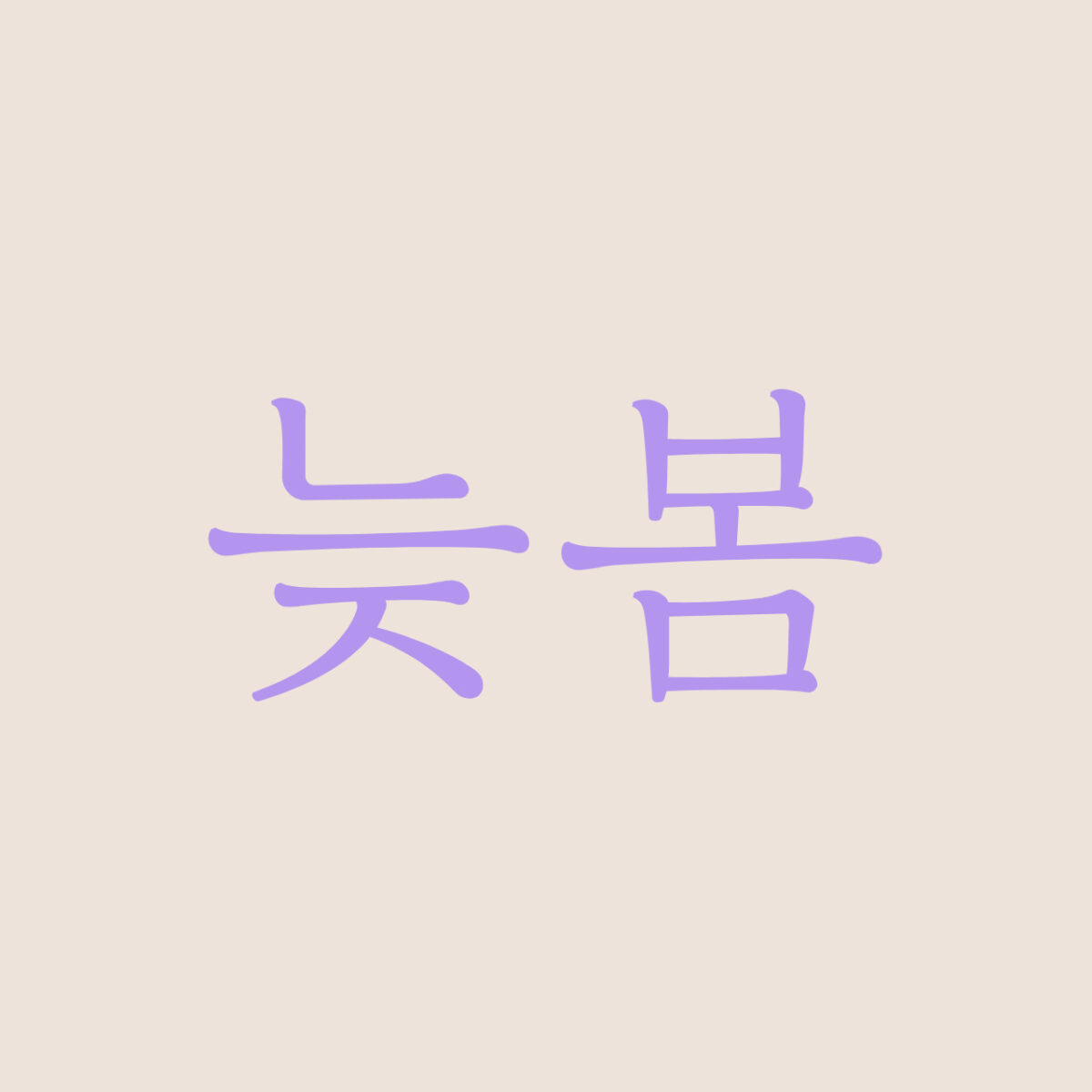
‘Sandoll 늦봄’은 붓글씨 특유의 감성을 부드럽게 살린 폰트입니다. 자연스러운 획의 꺾임과 손글씨의 필순을 따른 디자인으로, 정갈하고 정성스러운 느낌을 줄 수 있어요. 일반 Light, Medium 2종과 아주 가는 White, 붓 자국처럼 장식을 남긴 Black 2종까지 총 4종을 지원하여 다양한 스타일로 선택하여 사용할 수 있어요. 브로슈어나 포스터, 간행물 등에 사용하여 봄의 따뜻한 감성을 표현해 보세요.
2. 디엑스코리아 / DX봄바람
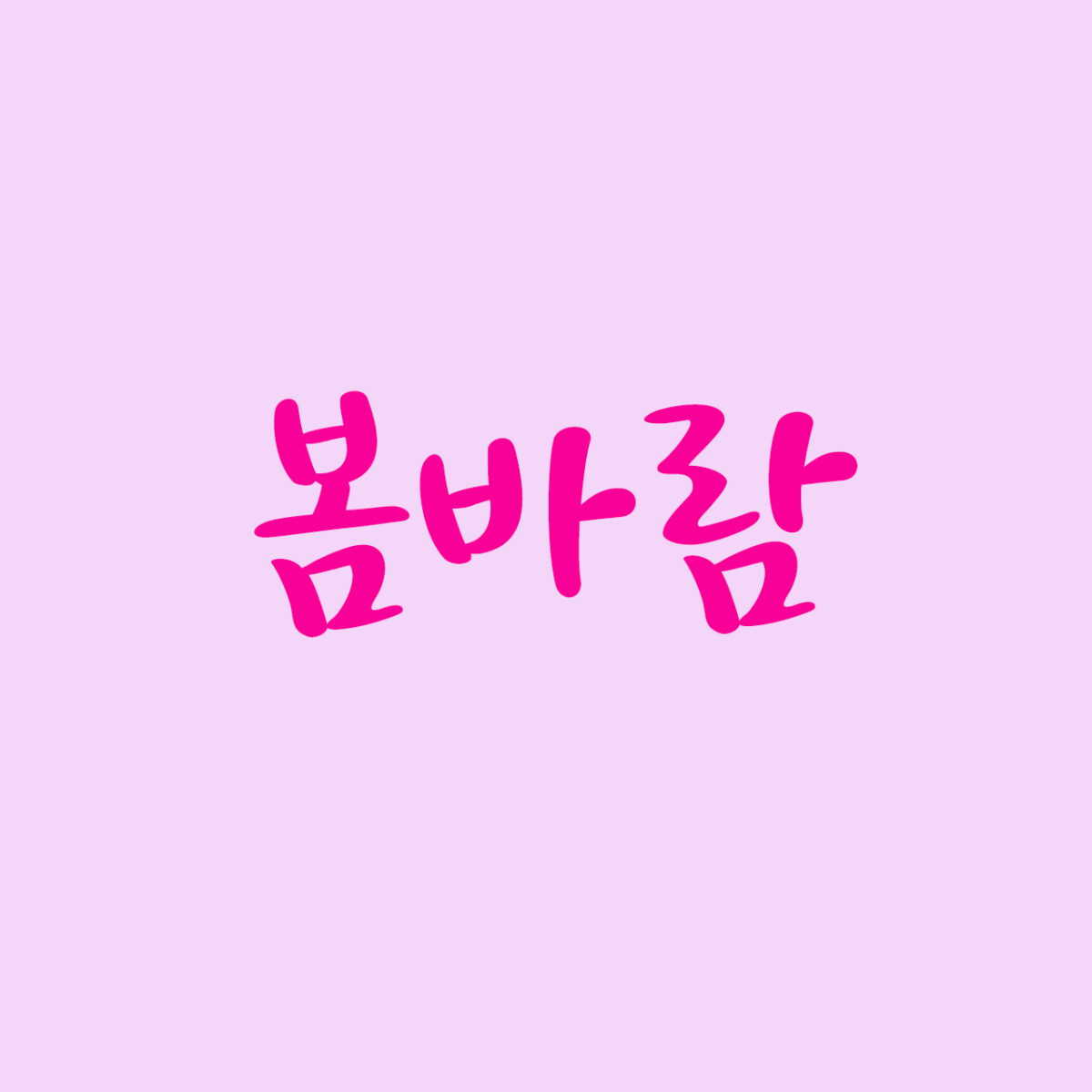
‘DX봄바람’은 이름 그대로 살랑거리는 봄바람이 느껴지는 손글씨 폰트입니다. 가늘고 두꺼운 획이 적절하게 조화를 이루어 자연스럽고 편안한 인상이 느껴져요. 방송 자막이나 타이틀, 봄과 관련된 행사 포스터나 현수막에 사용하는 것을 추천해요!
3. 타입세트컴퍼니 / TSC봄을닮아
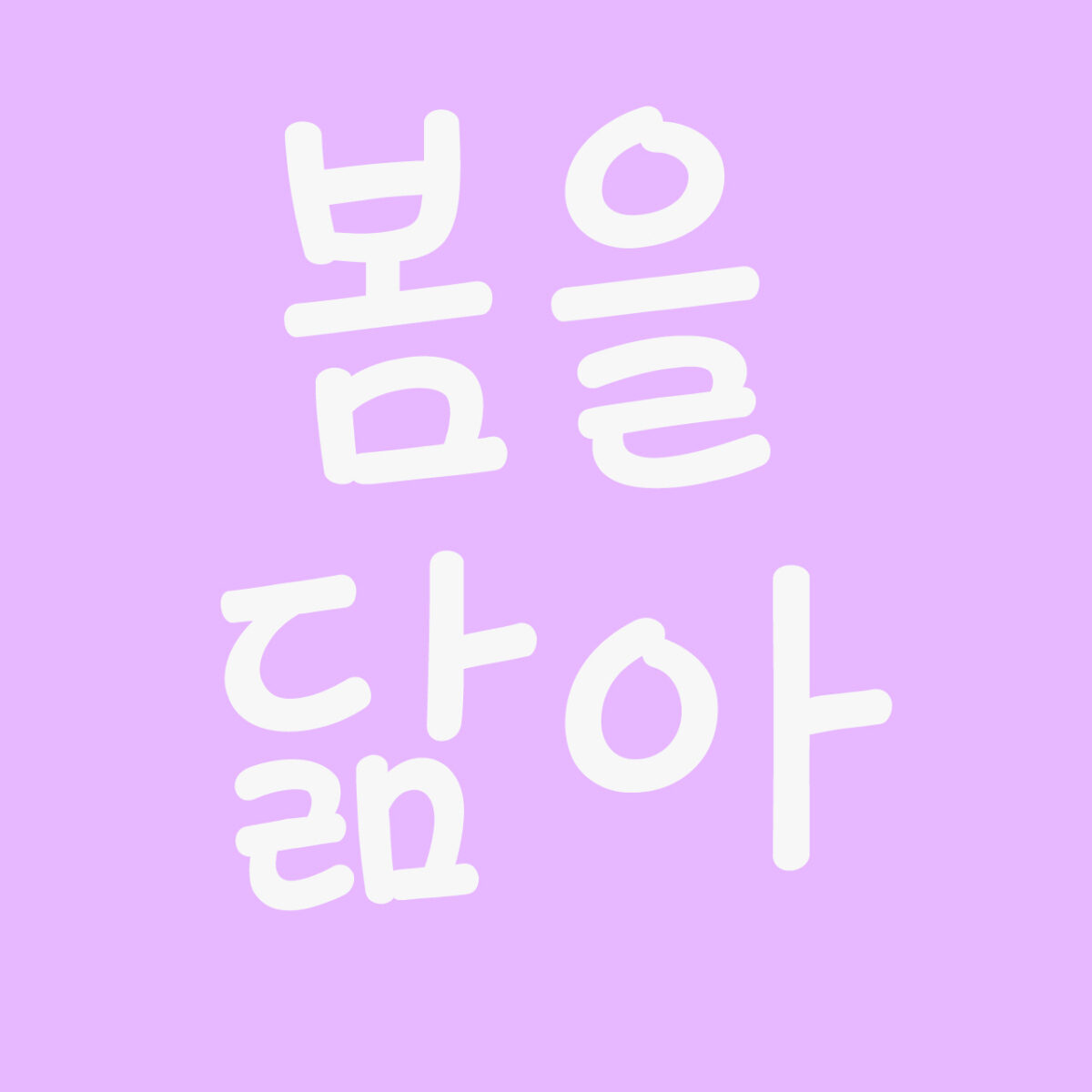
‘TSC봄을닮아’는 흘려 쓴 펜글씨의 특징이 담겨있는 귀엽고 아기자기한 폰트입니다. ‘ㅁ, ㅊ, ㅎ’ 등의 자소에서 직접 손으로 쓴 획순이 남아있어 자연스럽고 곡선에서 감성적인 인상이 느껴져요. 산돌구름 모바일 앱을 설치하면 모바일 환경에서도 사용 가능하니 봄맞이 기분 전환 폰트로 만나보세요!
4. 티랩 / Tlab따단산스
Tlab따단산스는 재미있는 율동감을 가진 폰트입니다. 기존 오블리크 서체와 반대 방향으로 기울어진 것이 특징으로, 자유로운 곡선과 독특한 기울임꼴이 주는 개성이 뛰어난 폰트예요! 글자 자체의 율동감에서 음악을 연상시키는 느낌이 들어 봄 시즌에 열리는 페스티벌이나 축제의 홍보물에 활용하면 잘 어울립니다. 따단산스와 함께 즐거운 봄 기운을 만끽해보세요!